Font chữ kéo dài là nhóm phông chữ đặc biệt thuộc dòng Script và Calligraphy sở hữu các đường râu chữ, nét móc vươn dài hoặc các đường lượn đuôi mềm mại ở đầu và cuối ký tự. Với khả năng tạo nên nhịp điệu thị giác bay bổng và đậm chất biểu cảm, kiểu chữ này giúp các kiến trúc sư, nhà thiết kế thổi hồn vào các bản vẽ phối cảnh biệt thự sinh thái, sảnh đón tiếp resort sang trọng hay bộ nhận diện thương hiệu homestay ven biển.
Đường nét uốn lượn bay bổng và kỹ thuật kéo đuôi chữ của font chữ kéo dài
Điểm cuốn hút của font chữ kéo dài nằm ở nghệ thuật kéo dài các nét liên kết chữ cái một cách hữu cơ, tạo cảm giác như dòng chảy tự nhiên của ngòi bút lông hoặc dải lụa mềm mại trong không gian.
Sự ổn định về mặt cảm xúc của dòng font này giúp truyền tải thông điệp về sự nhẹ nhàng, tinh tế và phong cách sống thi vị. Khi kết hợp cùng các bề mặt vật liệu kiến trúc hiện đại như kính cường lực mờ, kim loại mạ vàng gương hay gỗ óc chó tự nhiên trong các căn nhà lắp ghép cao cấp, phông chữ kéo dài tạo nên điểm nhấn nhẹ nhàng, làm dịu đi cảm giác khô cứng của các khối kết cấu kim loại.
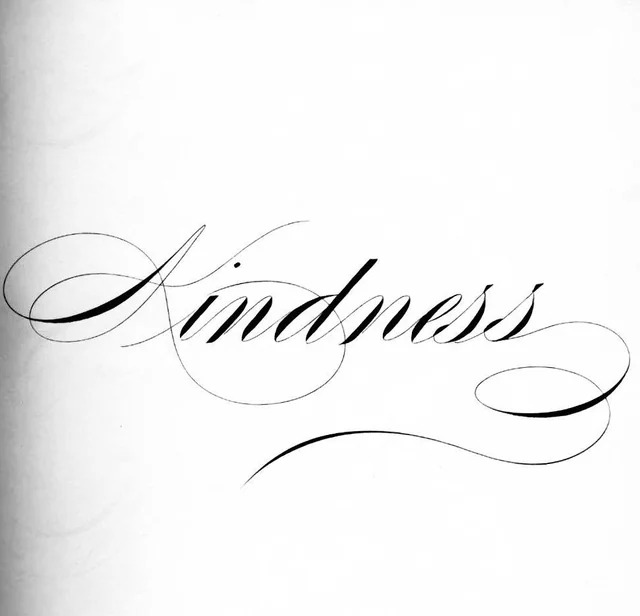
| Phân loại phong cách | Calligraphy / Flourished Script / Swash Display |
| Mục đích phù hợp | Biển tên villa, thiệp sự kiện sang trọng, logo chữ ký |
Tư vấn từ chuyên viên: Font kéo dài sở hữu các đường nét uốn lượn có biên độ rộng. Để bản thiết kế đạt hiệu quả thẩm mỹ tốt, bạn chỉ nên sử dụng phông chữ này cho các tiêu đề chính, tên thương hiệu hoặc cụm từ điểm xuyết ngắn.
03 Ứng dụng font chữ viết tay kéo dài vào công trình thực tế
Nhờ vẻ ngoài thanh lịch và tính gợi cảm xúc phong phú, bộ phông chữ này mang lại giá trị thực tế lớn trong khâu tạo điểm nhấn cho các công trình hiện đại:
- Biển hiệu mặt tiền cho Villa và Homestay Nghỉ dưỡng: Những nét chữ kéo dài đuôi của phông chữ rất ăn ý khi gia công chữ nổi bằng inox vàng gương lồng đèn LED hắt sáng chân, giúp mặt tiền căn nhà lắp ghép nghỉ dưỡng toát lên vẻ duyên dáng và quý phái.
- Bìa hồ sơ ý tưởng kiến trúc: Sử dụng Font chữ viết tay kéo dài cho tên dự án hoặc lời tựa đầu trang giúp tập hồ sơ trông như một ấn phẩm thiết kế mang tính nghệ thuật cao, tạo thiện cảm lớn với các chủ đầu tư.
- Hệ thống biển tên phòng và bảng chào mừng nội khu: Phông chữ này khi khắc laser chìm trên gỗ tự nhiên hoặc in trên kính mờ sẽ giúp không gian hành lang và sảnh đón tiếp toát lên chất nghệ thuật tao nhã, mang lại cảm giác được chào đón ân cần cho du khách.
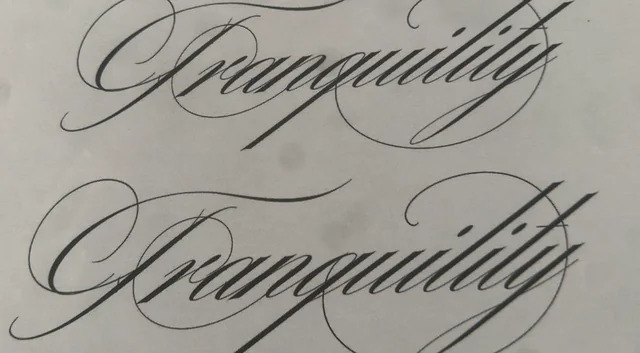
03 Lưu ý bố cục font chữ kéo dài đuôi giữ trọn tính mạch lạc
Để khai thác hiệu quả vẻ đẹp của dòng font uốn lượn này mà không gây cảm giác rối mắt cho bản vẽ, người thiết kế nên lưu tâm một số kinh nghiệm sau:
- Chủ động chọn nét đuôi qua bảng ký tự: Trong các phần mềm thiết kế chuyên nghiệp như Illustrator hay Photoshop, bạn hãy mở bảng Glyphs để lựa chọn các ký tự có độ kéo dài đuôi phù hợp với khoảng trống của bố cục, tránh để nét đuôi va chạm vào các chi tiết đồ họa khác.
- Kiểm soát khoảng cách dòng: Do các nét vươn dài có thể lấn sang không gian của dòng chữ bên dưới, bạn nên nới rộng khoảng cách giữa các dòng văn bản để câu chữ giữ được sự thoáng đãng và minh bạch.
- Tránh viết hoa toàn bộ cụm từ: Các ký tự hoa của phông chữ này có độ xoắn và vươn dài rất rộng. Việc viết hoa liên tiếp nhiều chữ cái sẽ làm các nét móc đè lên nhau, gây mất trật tự thị giác và khiến câu văn trở nên khó đọc.
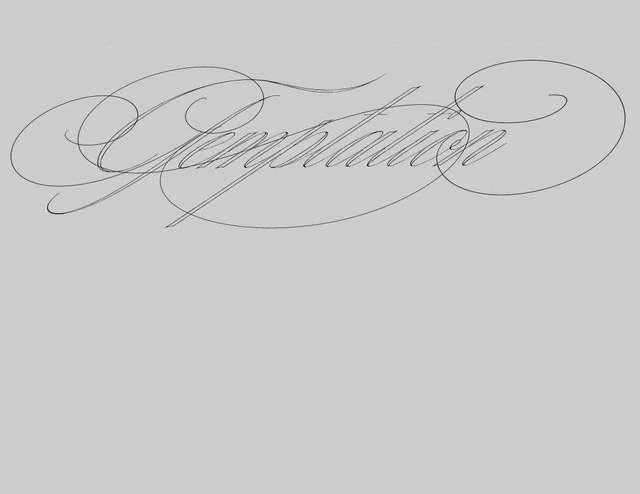
FAQs – Thắc mắc thường gặp khi sử dụng font chữ kéo dài
1. Font chữ kéo dài có dùng được trên ứng dụng Canva không?
2. Làm sao để gõ được các nét đuôi kéo dài dài hơn ở cuối từ ngữ?
Nhiều bộ phông hỗ trợ các ký tự thay thế (Alternates) ở cuối từ. Trong Photoshop hoặc Illustrator, bạn chỉ cần bôi đen chữ cái cuối cùng hoặc mở bảng Glyphs để chọn ký tự có đuôi uốn dài theo ý muốn.